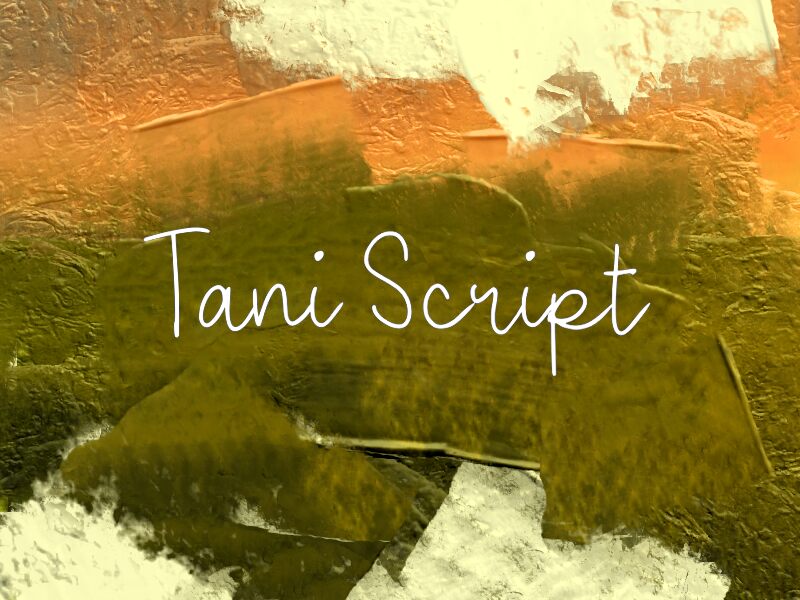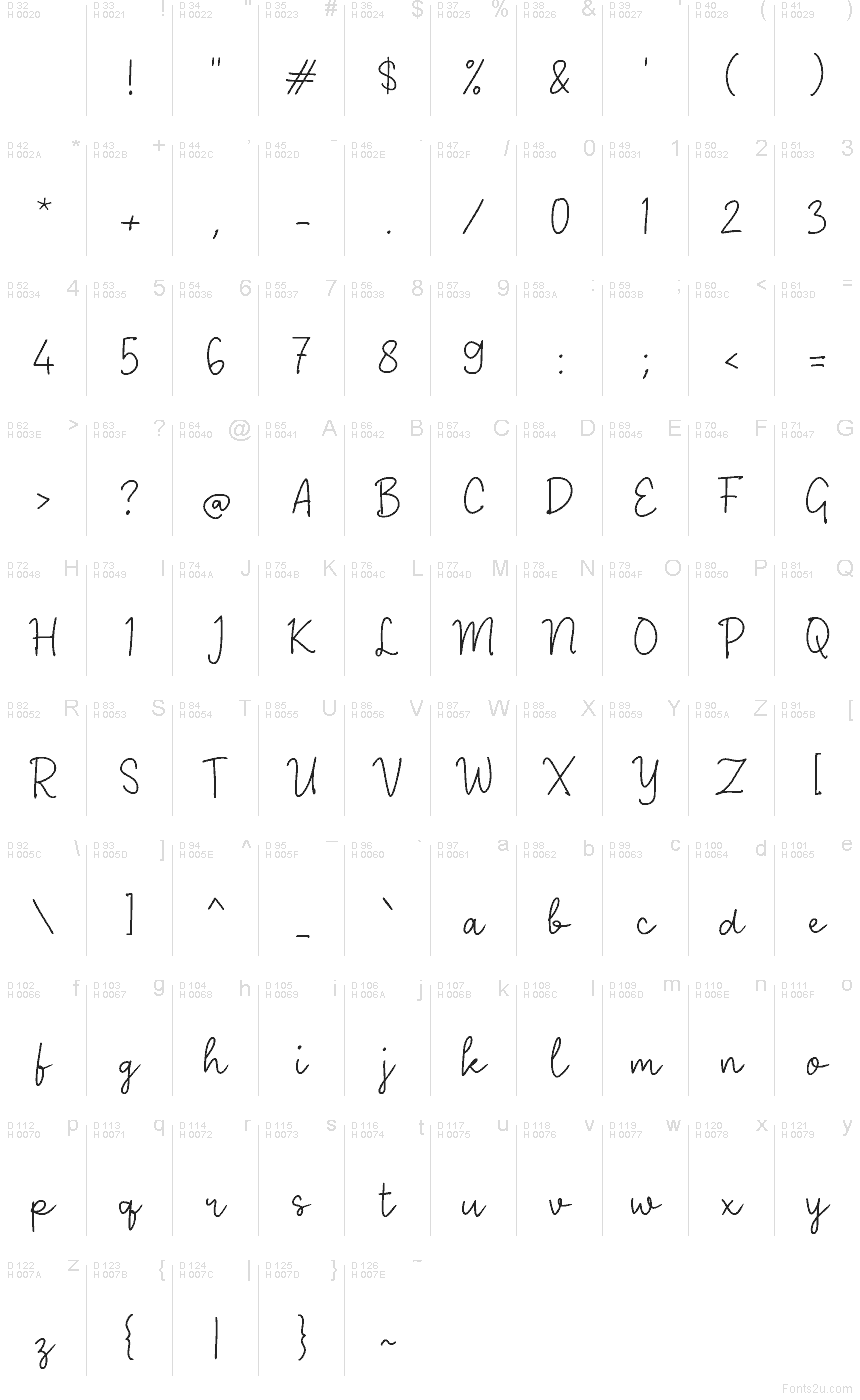
Tani Script
Tani Script di Wep è un font scritto a mano gratuito con il ritmo sciolto di una firma personale veloce. Le lettere si muovono con tratti lunghi e ariosi, forme arrotondate e aperte e un T iniziale alto, conferendo al carattere un aspetto informale e stiloso, lontano dalla rigidità della calligrafia tradizionale.
È ideale per la grafica dei social media, un branding informale, il packaging, le citazioni su immagini e brevi titoli di blog o video in cui il tocco umano conta più della formalità. Essendo un font gratuito, funziona bene anche per targhette, titoli e monogrammi semplici, poiché le giunture fluide e il ritmo naturale rendono credibile anche la parola più breve.